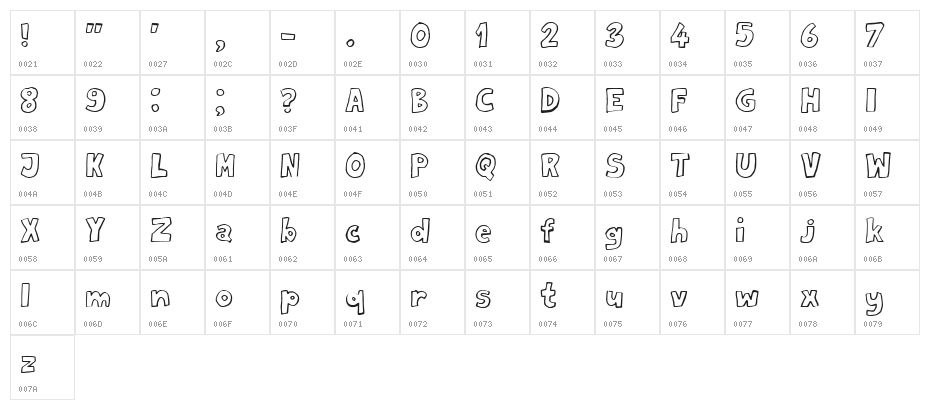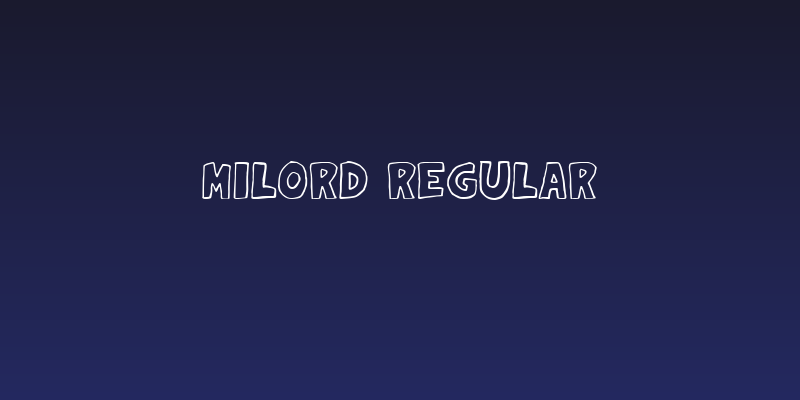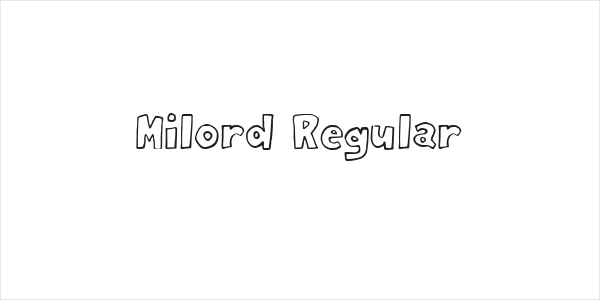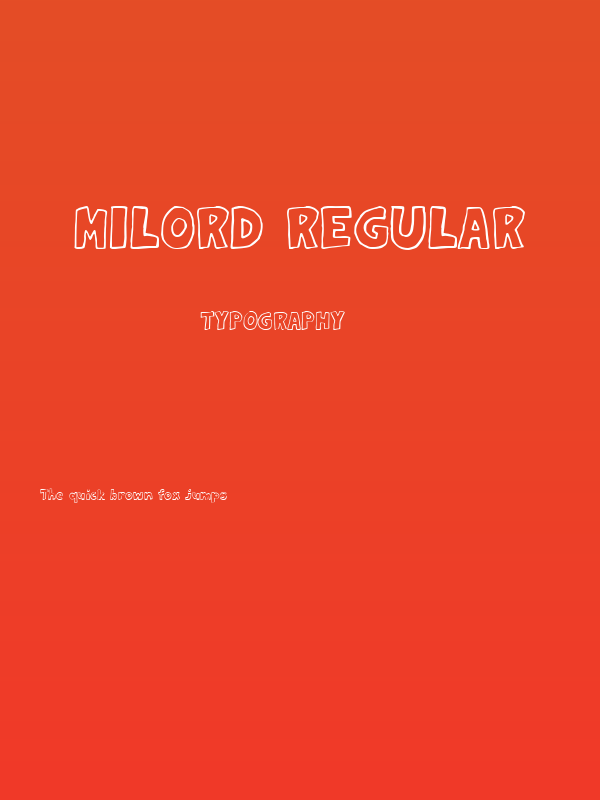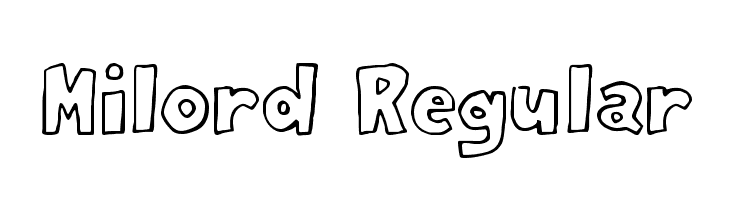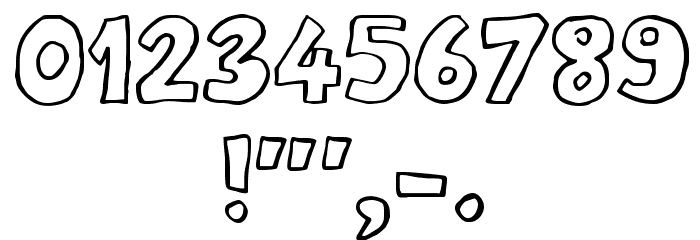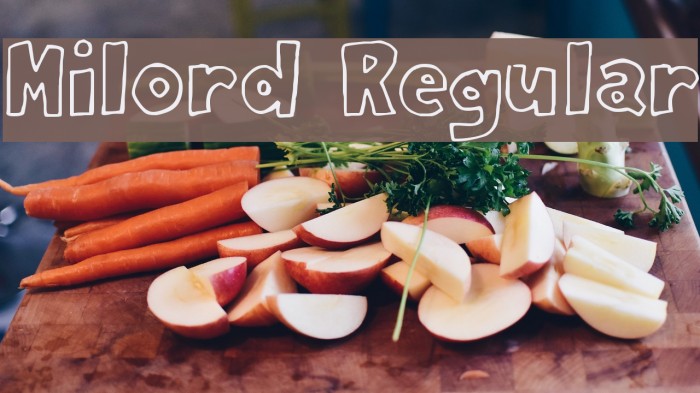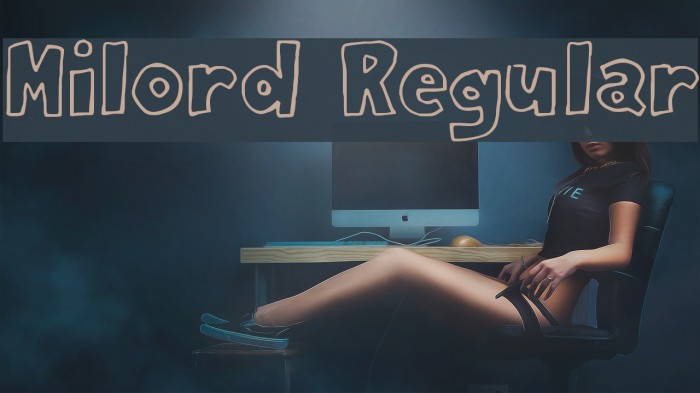
Milord Regular Font
Vladimir Nikolic - www.coroflot.com/vladimirnikolic
| 全体的なスタイル | Playful, Whimsical |
| おすすめプロジェクト | Ideal for children's books, comic strips, playful branding, and casual invitations. |